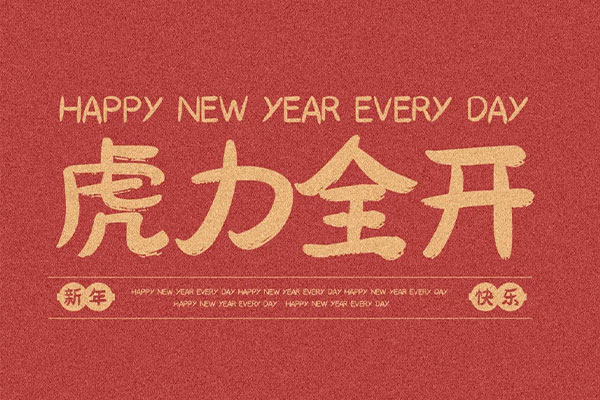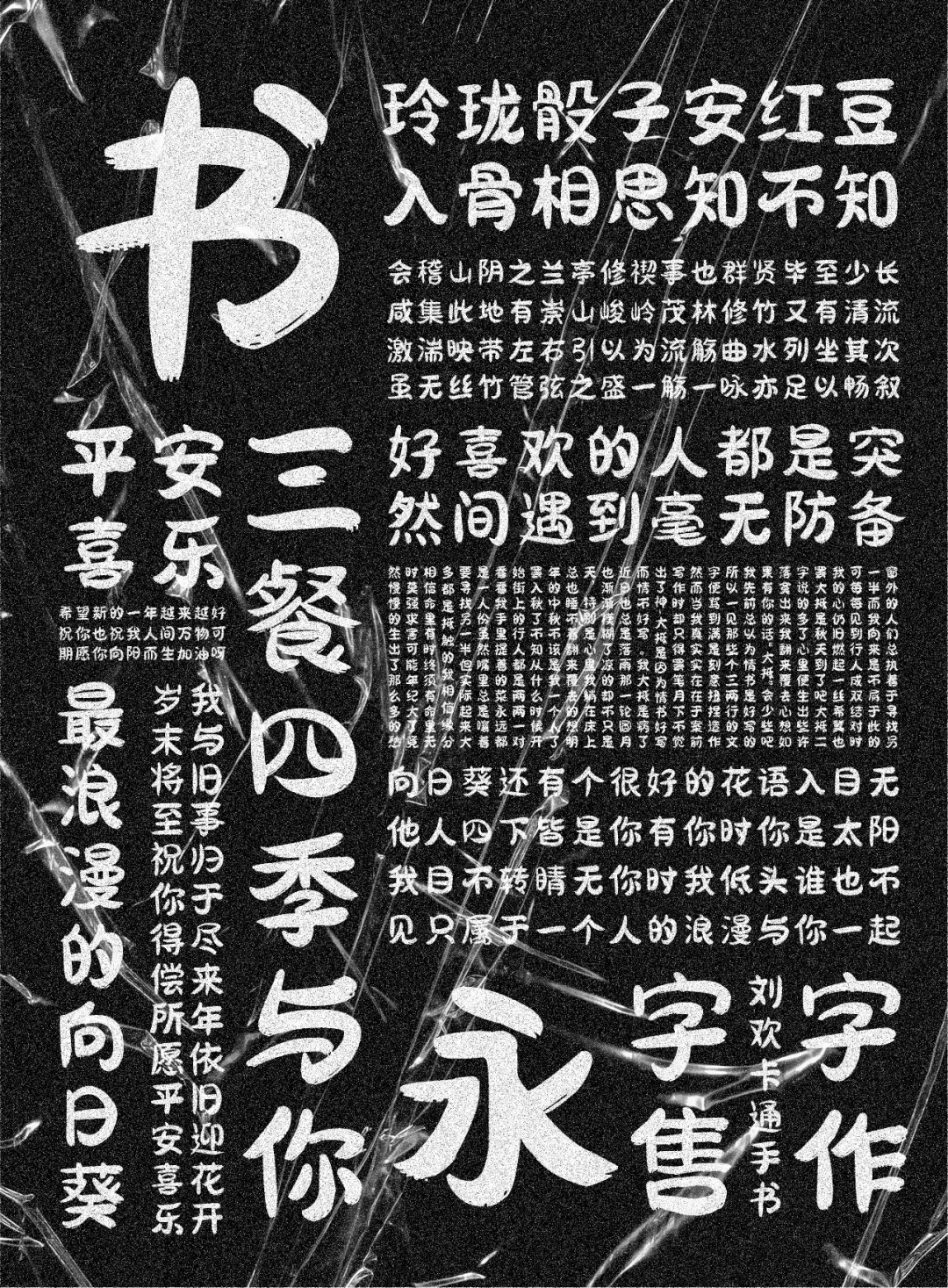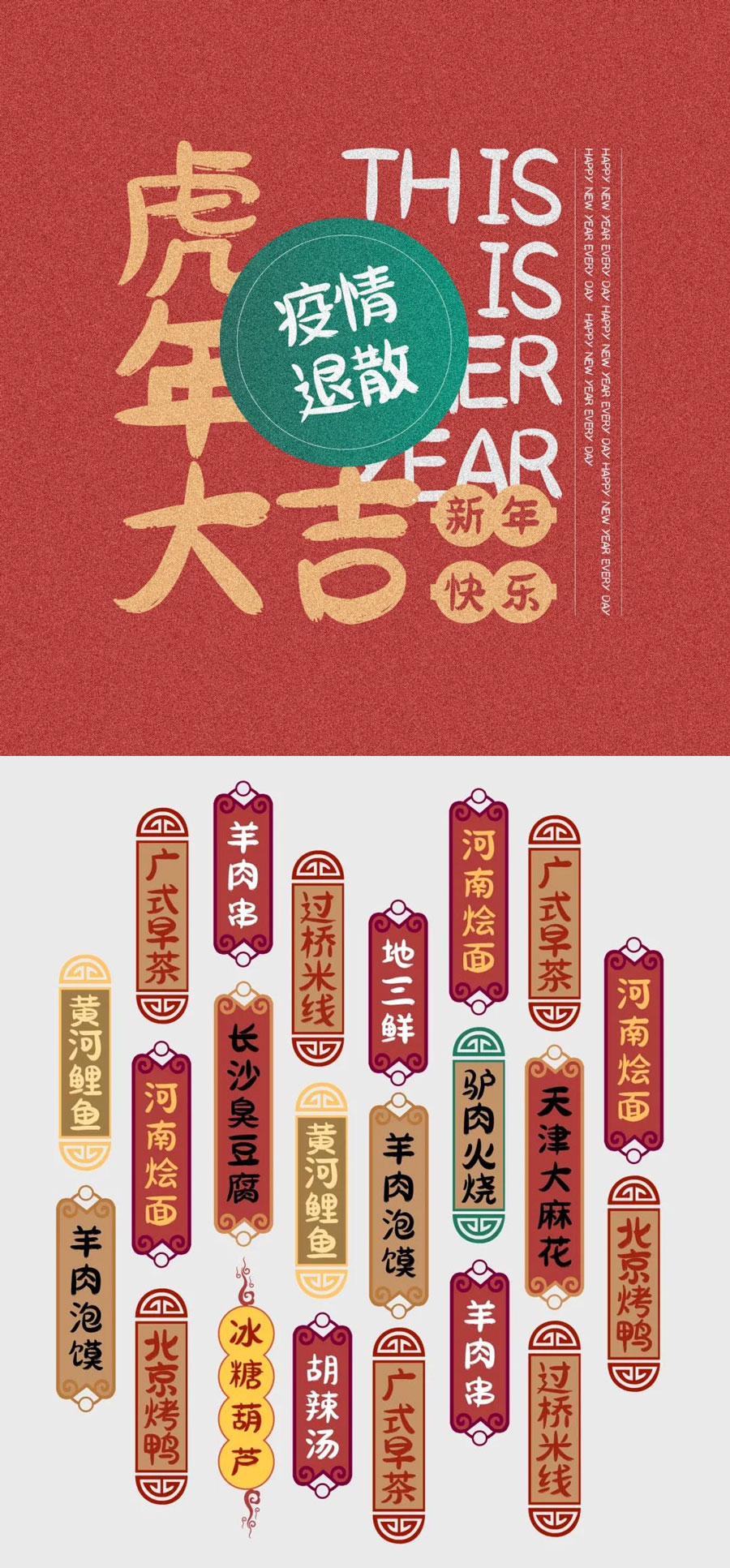
欢字卡通手书是中国大陆的刘欢同学创作的。他因为找不到合适的工作,闲暇之余便涂涂画画,萌生了做字体的想法。这款字体也是他的第一款中文字体。
欢字卡通手书包含了简体标准的6763字,不会出现缺字现象。作者在公众号上发布了这款字体,并声明可以永久免费商用。
这款卡通字体设计独特,以圆润的笔画为主,保留了少量的飞白,使得在屏幕上显示更加出色。
卡通字体不仅在视觉上给人带来愉悦的感受,而且还有着强烈的手写韵味。这种韵味使得这款字体在线下使用时也别具一格,让人眼前一亮。
卡通字体的使用场景非常广泛,不仅适合于各种数字和字母的组合,还可以用于一些短句或短文的呈现。当然,由于这款字体比较粗壮,不太适合太小的字体展示,因此在使用时需要根据具体情况进行调整。